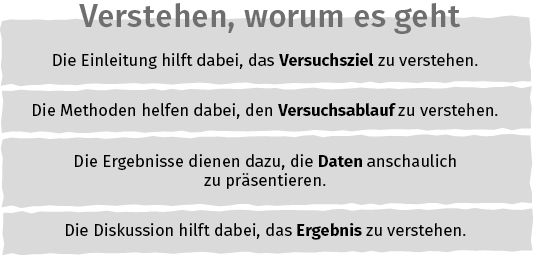
Minion Pro - und welche Grotesk?
ja, welche Nicht-Serifen-Schrift passt zur Minion – aber bitte nicht die Myriad ...! (Find ich langweilig ...)
Würde die TheSans passen, oder die Legacy Sans? Was meint ihr? Habt ihr noch bessere Vorschläge?
Das Ganze ist für ein Buch mit Erzählungen aus mehreren Ländern.
»Nature« mischt die Minion mit der Agenda und der Diverda Sans – für den naturwissenschaftlichen Hintergrund von »Nature« finde ich das eigentlich eine ziemlich spannende Mischung, muß ich sagen. Mir persönlich gefällt es recht gut! :P
Ein klassisch, bewährter Mixpartner wäre die FF Meta (die Meta Condensed nicht vergessen)
danke für die Tipps. Die Diverda sieht interessant aus.
ja an die Meta hatte ich auch schon gedacht.
Der Verlag hat mir die Minion vorgegeben und lässt mir frei, was ich für Überschiften nehme. Sie finden die Legacy Sans nicht schlecht für Überschriften.
Nun überleg ich halt, was ich denn davon halte.
Es geht, wie gesagt, um ein Buch mit kurzen Erzählungen aus China und aus Japan.
Die Kombination aus Meta und Minion ist die Hausmischung von Gräfe und Unzer ... ist vielleicht ein wenig zu "ratgeberisch" für Erzählungen. Ich würd vielleicht mal an was Schmal-DINinges denken.
Ich würde die Minion Pro mit der Syntax mischen. Die Syntax ist eine charakterstarke Schrift, die eine Nuance nach rechts geneigt ist und
deren runde und diagonale Striche optisch mit rechtwinkligen Abschlüssen endet. Die Syntax vereint die Klarheit der Groteskschriften mit der Wärme
und Lesbarkeit der Renaissance-Antiqua.
Ich lass das alte Thema mal wieder aufleben, statt extra ein neues Thema zu starten.
Ich schreibe gerade an einem Buch, für das ich auch ein paar Illustrationen selbst basteln werde. Das Buch (ein Ratgeber für Biologen) wird voraussichtlich in Minion Pro gesetzt, der Verlag wünscht sich für die Illustrationen eine Serifenlose wie "Meta o.ä." Nun habe ich Meta nicht und frage mich, ob ich mich mit der Fira Sans durchmogeln kann. Für andere kleine Projekte habe ich die immer ganz gerne benutzt, da sie aber für den Webauftritt designt wurde, ist sie wahrscheinlich für den Buchdruck eher ungeeignet. Ich mag allerdings dass sie etwas größer wirkt läuft als die Meta.
Ich habe mal eine Abbildung als Beispiel angehängt. Ich würde mich über Kritik und Tipps freuen.
ich hab die Fira Sans (Light) im letzten Semester für ein Magazin genutzt und das hat eigentlich ganz gut geklappt. Das Schriftbild ist ein Hauch unruhig, weil die Strichstärken der Buchstaben etwas zu „schimmern“ scheinen, aber das würde ich auf den billigen Druck und nicht auf die Schrift schieben. Außerdem wirst du vermutlich ja nicht auf einem gestrichenen/glatten Papier drucken, da sollte das dann noch weniger auffallen (falls es doch an der Schrift selbst liegt).
Zu deiner Abbildung: Ich finde es nicht so glücklich, dass die „Überschrift“ halb in der ersten Box steht, denn sie gehört ja zur ganzen Abbildung und nicht nur zum ersten Block. Oder?
PS: Du kannst die Schrift zum Testen ja auch einfach mal auf einem ordentlichen Laserdrucker ausgeben, da kann man das auch schon ganz gut beurteilen. Vor allem auch wegen der richtigen Größe. Ich hab die Erfahrung gemacht, dass man die Fira kleiner setzen kann, als man vielleicht erstmal annähme …
vielen Dank für deinen Erfahrungsbericht. Ich habe auch gemerkt, dass man die Fira kleiner setzen kann. Das macht Sie recht attraktiv für mich. Das Buch wird ein kleines UTB-Taschenbuch (etwa B6) mit einer relativ kleinen Schriftgröße. Und du hast Recht, es wird ein kräftiges, nicht glattes Papier. Nach einem ersten Drucktest bin ich soweit recht zufrieden.
Zur Abbildung: Da gebe ich dir völlig Recht. Ist auch noch in Arbeit. Ich will die Überschrift wahrscheinlich handschriftlich haben, so dass sie halb über die Kästen gemalt wirkt. Das soll sich durch alle Abbildung ziehen. Fira käme dann nur bei den Abbildungen zum Einsatz, wo Listen oder längere Texte auftauchen.
Hm … wenn der Verlag sich ne Serifenlose wünscht, könnte ich mir vorstellen, dass die mit ner (zusätzlichen) Handschriftlichen Probleme haben. Und drei Schriften zu kombinieren ist vielleicht auch nicht die beste Lösung, vor allem wenn die Unterscheidung zwischen Handschrift und Sans nicht vom Inhalt getragen bzw. durch diesen begründet ist sondern nur nach Textlänge.
Finde ich als Leser (und als Gestalter) komisch, wenn die beiden Schriften so „sinnlos“ auftreten. Ich würde mir dann eher alle Abbildungen im Skizzen-Stil mit (echter?) Handschrift oder technischere/„ordentlichere“ Abbildungen mit ner Sans.
Alternativ evtl. Text in Serif; Überschriften, Abnildungsnummer/-titel etc. in Sans und alle Texte, die in/auf einer Abbildung stehen handschriftlich.
Hm, gutes Argument. Ich muss zugeben, die Serifenlose bekam erst eine Notwendigkeit als ich eine Abbildung mit viel Text hatte. Das finde ich handgelettert eher mühsam zu lesen. Vielleicht kann ich die paar textlastigen Abbildungen zu grau unterlegten Kästen umwandeln (dann entweder mit der Fira oder vielleicht sogar besser mit ner Minion Bold) und den Rest tatsächlich komplett handlettern. Das spreche ich mal an. Danke für den Einwand.
Mir ging es dabei mehr um die Rolle der Fira in der Abbildung als um die Abbildung selbst (und darauf bezog ich mich als ich Tobi Recht gegeben habe). Mir gefällt aber mittlerweile die Idee es komplett handzulettern und die textlastigen Abbildungen anders darzustellen.